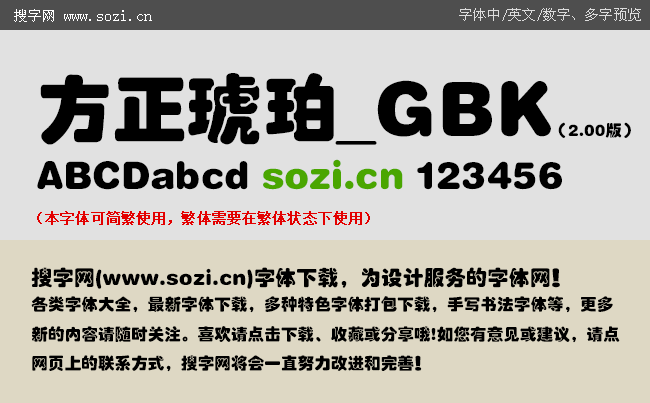
方正琥珀_GBK
搜字網(wǎng)提供一款方正琥珀_GBK中文字體下載,方正琥珀_GBK是一款非常端正的中文字體,方正琥珀柔滑細(xì)膩,強(qiáng)壯有力,清晰醒目,,GBK碼包含字體更全,適合應(yīng)用于廣告設(shè)計(jì)、名片設(shè)計(jì)、包裝印刷、兒童產(chǎn)品設(shè)計(jì)等應(yīng)用。
• 風(fēng)格類別: 琥珀體